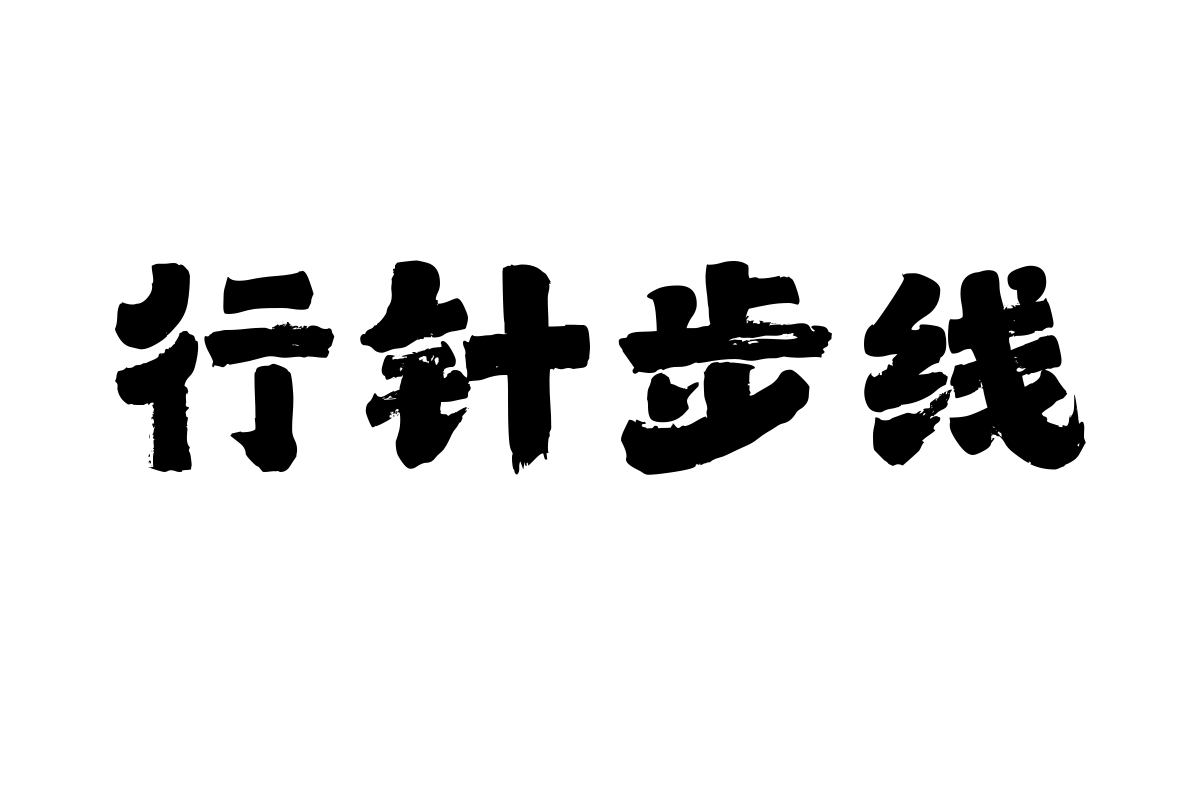
山海鸿墨手书w是一款具有独特艺术风格的字体,它结合了传统的书法韵味和现代的设计感。这款字体的特点是笔画流畅自然,线条粗细变化丰富,既有古典的韵味,又不失现代的时尚感。它的字形结构严谨,每个字都充满了力量和美感,给人以视觉上的享受。
山海鸿墨手书w适用于各种设计场景,如广告、海报、书籍封面、网页等。它不仅可以用于文字排版,还可以作为图形元素使用,为设计作品增添独特的艺术气息。